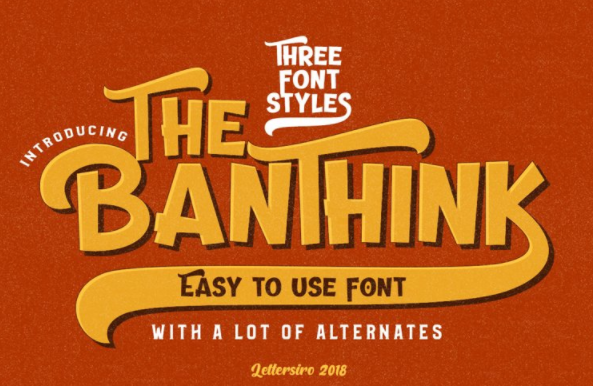
Мы только что запустили наш новый продукт. Мы создали игривый шрифт под названием Banthink Font, который выглядит круто и современно-винтажно.
Этот шрифт отлично подходит для логотипов, плакатов, одежды, брендинга, вечеринок, приглашений и многих других классных дизайнерских проектов.
приглашений и многих других классных дизайнерских проектов. Banthink поставляется
с большим количеством альтернативных символов, а также с 3 стилями шрифта.